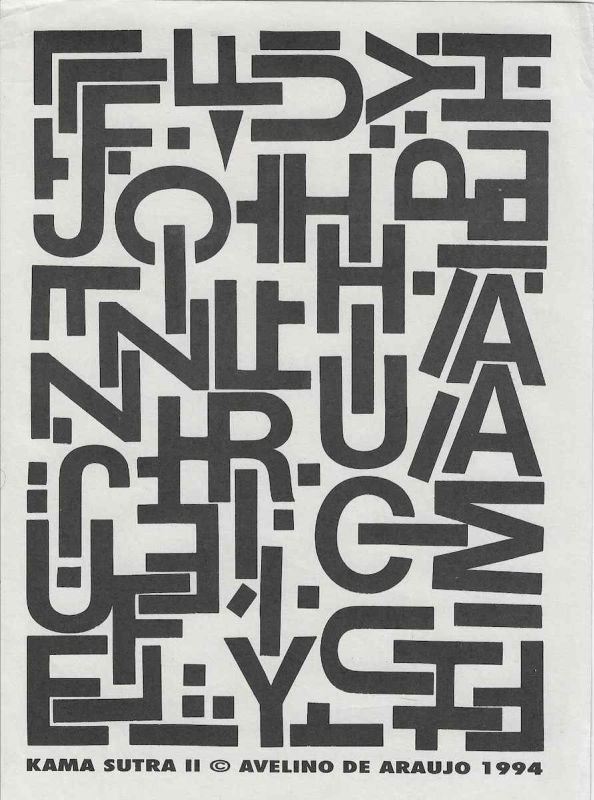
Kama Sutra II Pequeno é uma impressão gráfica de Avelino de Araújo realizada em 1994, vinculada à poesia visual, à poesia experimental, à arte conceitual, à tipografia e às investigações intersígnicas relacionadas ao campo do Poema Processo.
Kama Sutra II Pequeno é uma impressão gráfica de Avelino de Araújo realizada em 1994, vinculada à poesia visual, à poesia experimental, à arte conceitual, à tipografia e às investigações intersígnicas relacionadas ao campo do Poema Processo. A composição apresenta um campo vertical intensamente preenchido por letras maiúsculas, fragmentos tipográficos, pontos, quadrados, triângulos, barras e formas geométricas distribuídas em diferentes posições e orientações. Os caracteres aparecem girados, invertidos, inclinados, sobrepostos e encaixados, formando uma estrutura densa que impede a leitura linear convencional. O título Kama Sutra II indica a continuidade de uma série e orienta a interpretação da obra para o corpo, o erotismo, a sexualidade, o desejo, o contato e as múltiplas posições possíveis entre formas. Avelino de Araújo substitui os corpos humanos por letras e sinais gráficos. Os caracteres passam a funcionar como membros, troncos, articulações, gestos, aproximações, tensões e encaixes. As formas curvas sugerem flexões, abraços e movimentos corporais, enquanto as barras retas, ângulos e triângulos estabelecem direções, apoios, aberturas e relações espaciais. Algumas letras se aproximam ou se atravessam, criando associações visuais com posições corporais e encontros entre duas ou mais estruturas. A obra transforma o alfabeto em anatomia abstrata e converte a página em espaço de coreografia tipográfica. Diferentemente de uma frase ou poema verbal, a composição deve ser observada em várias direções. O olhar percorre a superfície, reconhece letras isoladas, perde sua identificação e volta a percebê las como imagens. Essa alternância entre leitura e visão constitui um dos principais procedimentos da poesia visual. O termo Pequeno pode indicar uma versão de formato reduzido, uma edição condensada ou uma variação menor dentro da série Kama Sutra. A indicação II reforça a existência de uma pesquisa continuada sobre corpo, escrita, deslocamento e organização de signos. A alta densidade dos elementos cria sensação de energia, movimento, contato e instabilidade, enquanto o contraste entre preto e fundo claro mantém a definição das formas. Kama Sutra II Pequeno pode ser compreendida como poema visual, escrita erótica abstrata, mapa corporal, composição tipográfica e documento conceitual. Na parte inferior aparecem a identificação KAMA SUTRA II, o símbolo de autoria, o nome Avelino de Araújo e o ano 1994. Palavras chave para indexação: Avelino de Araújo, Kama Sutra II Pequeno, Kama Sutra II, 1994, impressão gráfica, poesia visual brasileira, poema visual, poesia experimental, arte conceitual, Poema Processo, erotismo, sexualidade, desejo, corpo, posições corporais, letras como corpos, tipografia experimental, composição tipográfica, escrita visual, gesto, movimento, rotação, inversão, sobreposição, palavra imagem, texto imagem, semiótica, intersigno, comunicação visual, arte gráfica brasileira, múltiplo gráfico, arquivo de poesia visual, arte brasileira do século vinte.TEXT FOR THE SALSA PROGRAM IN ENGLISH: Kama Sutra II Small is a graphic print by Avelino de Araújo produced in 1994 and associated with visual poetry, experimental poetry, conceptual art, typography and intersemiotic investigations connected with the field of the Poema Processo movement. The composition presents a vertical field densely filled with capital letters, typographic fragments, dots, squares, triangles, bars and geometric forms distributed in different positions and orientations. The characters appear rotated, inverted, inclined, superimposed and interlocked, creating a dense structure that prevents conventional linear reading. The title Kama Sutra II indicates the continuation of a series and guides interpretation toward the body, eroticism, sexuality, desire, contact and the multiple positions that forms may occupy in relation to one another. Avelino de Araújo replaces human bodies with letters and graphic signs. The characters begin to function as limbs, torsos, joints, gestures, approaches, tensions and connections. Curved forms suggest flexion, embraces and bodily movement, while straight bars, angles and triangles establish directions, supports, openings and spatial relationships. Some letters approach, cross or penetrate one another, creating visual associations with bodily positions and encounters between two or more structures. The work transforms the alphabet into abstract anatomy and converts the page into a space of typographic choreography. Unlike a sentence or verbal poem, the composition must be observed in several directions. The eye moves across the surface, recognizes isolated letters, loses their identity and perceives them again as images. This alternation between reading and seeing is one of the principal procedures of visual poetry. The term Small may indicate a reduced format, a condensed edition or a smaller variation within the Kama Sutra series. The indication II reinforces the existence of an ongoing investigation into the body, writing, displacement and the organization of signs. The high density of the elements creates sensations of energy, movement, contact and instability, while the contrast between black and the light background preserves the definition of the forms. Kama Sutra II Small may be understood as a visual poem, abstract erotic writing, bodily map, typographic composition and conceptual document. The lower section contains the identification KAMA SUTRA II, the authorship symbol, the name Avelino de Araújo and the year 1994. Keywords for indexing: Avelino de Araújo, Kama Sutra II Small, Kama Sutra II, 1994, graphic print, Brazilian visual poetry, visual poem, experimental poetry, conceptual art, Poema Processo, eroticism, sexuality, desire, body, bodily positions, letters as bodies, experimental typography, typographic composition, visual writing, gesture, movement, rotation, inversion, superimposition, word image, text image, semiotics, intersign, visual communication, Brazilian graphic art, graphic multiple, visual poetry archive, twentieth century Brazilian art.
Impressão gráfica em tinta preta sobre papel claro, composta por grande quantidade de caracteres tipográficos e formas geométricas distribuídos por quase toda a área da folha. São visíveis letras maiúsculas como A, C, E, F, G, H, I, J, L, N, P, R, S, T, U, V, Y e outras formas parcialmente modificadas. Também aparecem pontos, quadrados, barras, pequenos retângulos e triângulos. Os caracteres apresentam diferentes tamanhos, espessuras e orientações. Muitos estão girados em noventa ou cento e oitenta graus, inclinados ou parcialmente unidos a outras letras. A disposição forma blocos compactos e reduz a presença de espaços vazios no interior da composição. Algumas letras mantêm leitura imediata, enquanto outras passam a funcionar como estruturas geométricas e fragmentos corporais. O conjunto apresenta forte contraste, ritmo irregular, alta densidade e leitura multidirecional. Na base encontra se a inscrição KAMA SUTRA II, seguida pelo símbolo de autoria, pelo nome AVELINO DE ARAÚJO e pelo ano 1994. O suporte apresenta ondulações, vincos, marcas de dobra, pequenas manchas, alterações de tonalidade e sinais de envelhecimento e manuseio. A peça pode ser classificada como poema visual, impressão de artista, múltiplo gráfico, estudo tipográfico, composição erótica abstrata e documento conceitual, sendo relevante para pesquisas sobre Avelino de Araújo, Poema Processo, poesia visual, corpo, sexualidade, erotismo, linguagem, tipografia, semiótica e produção gráfica brasileira.OBSERVATION TEXT IN ENGLISH: Graphic print in black ink on light colored paper composed of a large number of typographic characters and geometric forms distributed across almost the entire sheet. Capital letters such as A, C, E, F, G, H, I, J, L, N, P, R, S, T, U, V and Y are visible together with other partially modified forms. Dots, squares, bars, small rectangles and triangles also appear. The characters vary in size, thickness and orientation. Many are rotated ninety or one hundred and eighty degrees, inclined or partially joined to other letters. Their arrangement creates compact blocks and reduces the presence of empty space within the composition. Some letters remain immediately legible, while others function as geometric structures and bodily fragments. The composition presents strong contrast, irregular rhythm, high density and multidirectional reading. The lower section contains the inscription KAMA SUTRA II, followed by the authorship symbol, the name AVELINO DE ARAÚJO and the year 1994. The support presents undulations, creases, fold marks, small stains, changes in tone and signs of aging and handling. The piece may be classified as a visual poem, artist print, graphic multiple, typographic study, abstract erotic composition and conceptual document, making it relevant to research on Avelino de Araújo, Poema Processo, visual poetry, the body, sexuality, eroticism, language, typography, semiotics and Brazilian graphic production.
Kama Sutra II Small is a graphic print by Avelino de Araújo produced in 1994 and associated with visual poetry, experimental poetry, conceptual art, typography and intersemiotic investigations connected with the field of the Poema Processo movement.